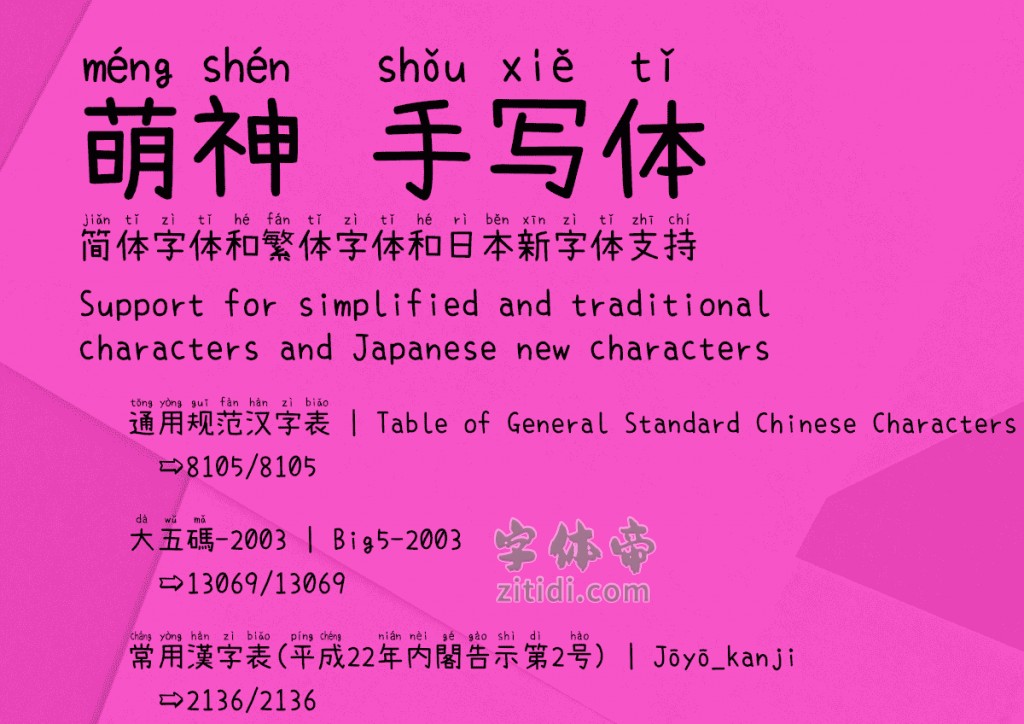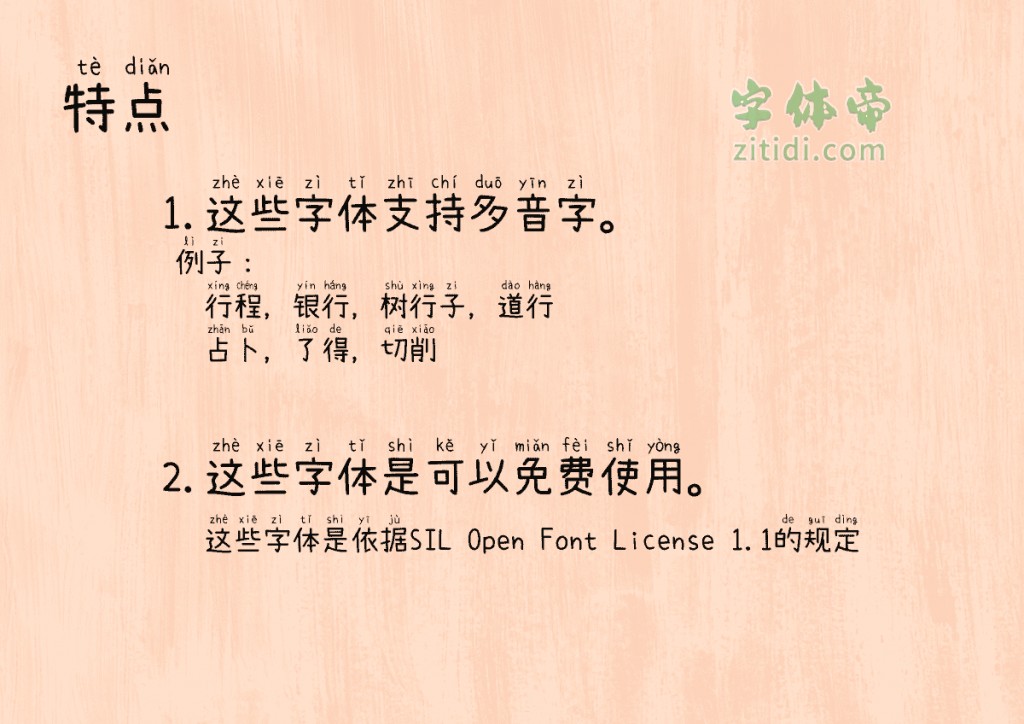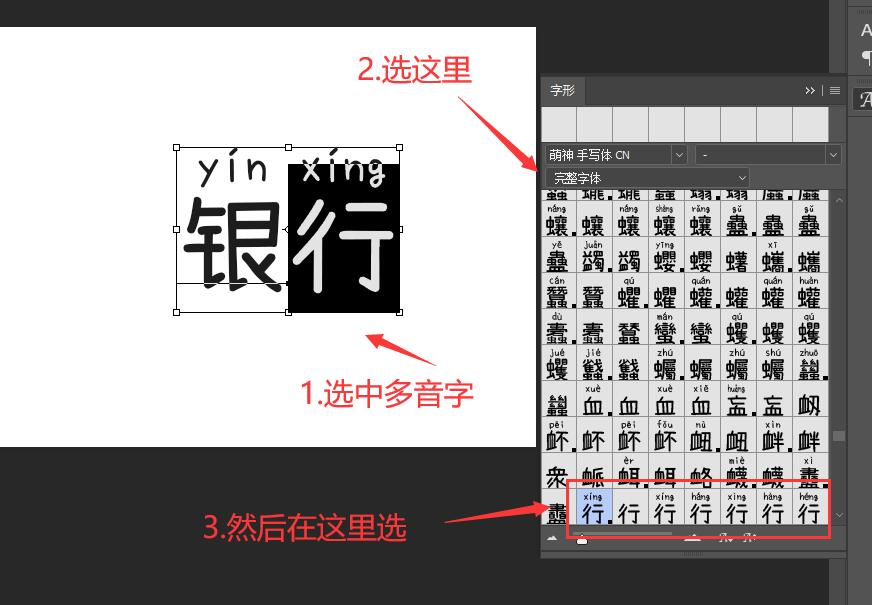
萌神手写体字体信息
萌神手写体
字体名称: 萌神手写体
字体风格: 手写体拼音体
萌神手写体是用于学习中国汉字的一款字体,是使用小赖字体进行改造而成的一款免费商用字体。 这是一种用来帮助学生更快地学习和阅读汉语的字体。基本上是可以显示日语、简体字和繁体字的字体,是在简体字和繁体字中加入拼音的字体的制作。
萌神手写体实现了上下文替换(feature of“rclt”at GSUB)以支持多音字。另外,还可以使用Unicode IVS(表意文字变体选择器)来切换到不同的拼音。